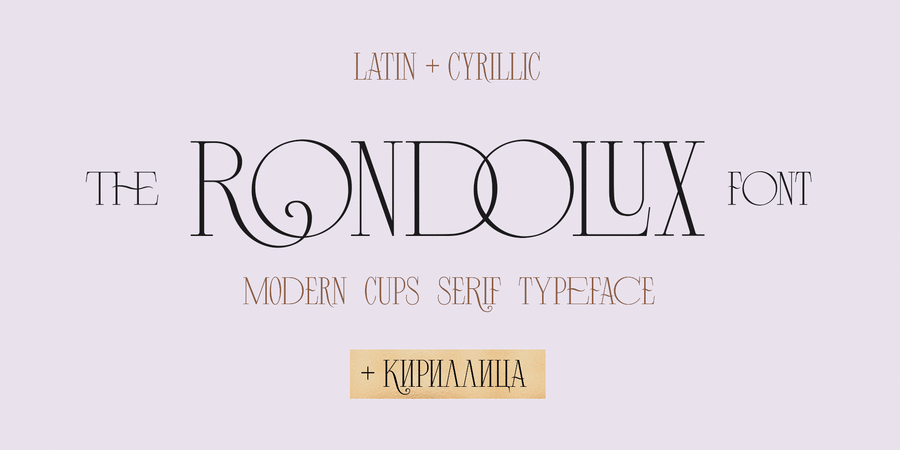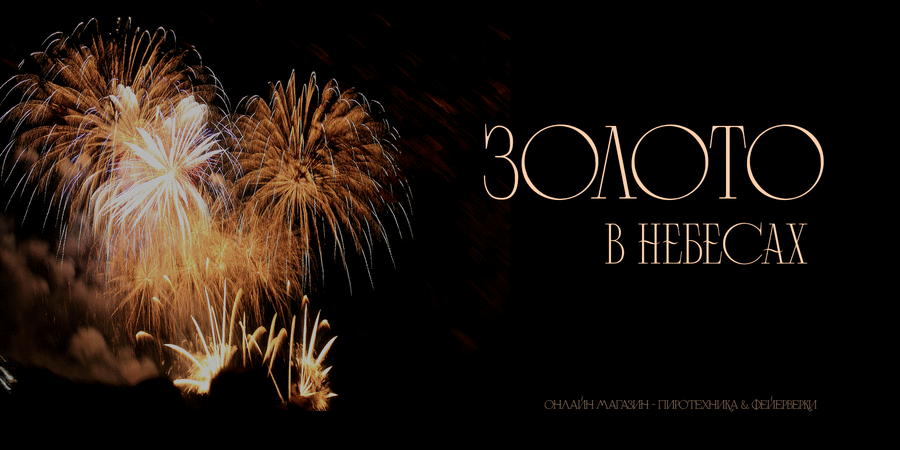
Опис шрифта Rondolux CyrillicШрифт Rondolux Cyrillic Serif — це стильний шрифт із засічками з вузькими рядковими й широкими великими літерами та безліччю лігатур. Цей шрифт ідеально підходить для чудових логотипів і назв, чудово поєднується з багатьма шрифтами та добре пасуватиме будь-яким проєктам, над якими ви працюєте. Ви можете використовувати вузькі або широкі гліфи, щоб зробити вашу типографію більш різноманітною.
Латинська частина шрифта Rondolux містить 38 лігатур, які можна отримати, ввівши цифру 1 після таких літер, як OC1 KO1 Lu1... Кирилична частина шрифта Rondolux містить 27 лігатур.
Багатомовна підтримка 32 мов: латинські гліфи для африкаанс, албанської, баскської, боснійської, каталонської, датської, голландської, англійської, естонської, фарерської, філіппінської, французької, галісійської, індонезійської, ірландської, італійської, малайської, норвезького букмолу, португальської, Словенська, іспанська, суахілі, шведська, турецька, валлійська, зулу.
А кириличні гліфи підтримують білоруську, болгарську, українську, казахську та російську мови.
Шрифт розробила Ірина Двілюк у 2022 році.
Асоціації з сімейством шрифтів Rondolux CyrillicОсобистість і характер гарнітури:
салонний, урочистий, дзвінкий, благородний, якісний, культурний, гострий, ностальгічний, старомодний, багатий, консервативний, світський, сріблястий, майстерний, розкішний, дорогий, ефектний, срібний, джентльменський, пафосний, крихкий, прозорий, тонкий, скляний, гнучкий, пластичний, елітний, модний, добірний, худий, красивий, ювелірний, витончений, виразний, характерний, художній, сексуальний, колючий, блискучий, глянцевий, естетський, міський, пристрасний, прекрасний, вишуканий, ексцентричний, химерний, динамічний, артистичний, гармонійний, технічний, освічений, гламурний, історичний, елегантний, епічний, амбітний, римський, видовищний, грандіозний, великий, величний, кінематографічний, монументальний, мотивуючий, фантастичний, золотий, дорогоцінний, романтичний, легкий, повітряний, традиційний, рівний, класичний, аристократичний, святковий, ввічливий, акуратний, музичний, манірний, жіночний, бальний, комільфо, пристойний, ошатний, граціозний, весільний, творчий, весняний, гордий, естетичний, знаменитий, оригінальний, цікавий, яскравий, інтимний, невагомий
вино, ресторан, одяг, сукня, свято, весілля, комільфо, готель, музей, розкіш, срібло, золото, годинник, мода, бутік, преміум, мистецтво, пейзаж, парфумерія, краса, косметика, прикраса, ювелір, коштовності, сервіровка, парфуми, Місто, дизайн, АСМР, гламур, кіно, видовище, тату, татуювання, балет, архітектура, живопис, Трофей, нагорода, захід сонця, кохання, романтика, опера, виставка, гравірування, салон, музика, бал, квіти, подарунки, торт, десерт, перукарня, весна концерт, художник, поезія, діамант, графіка, ілюстрація, інтер'єр, люкс, Модель, туфлі, каблук, театр, кафе, взуття Гарнітура асоціюється з віком: